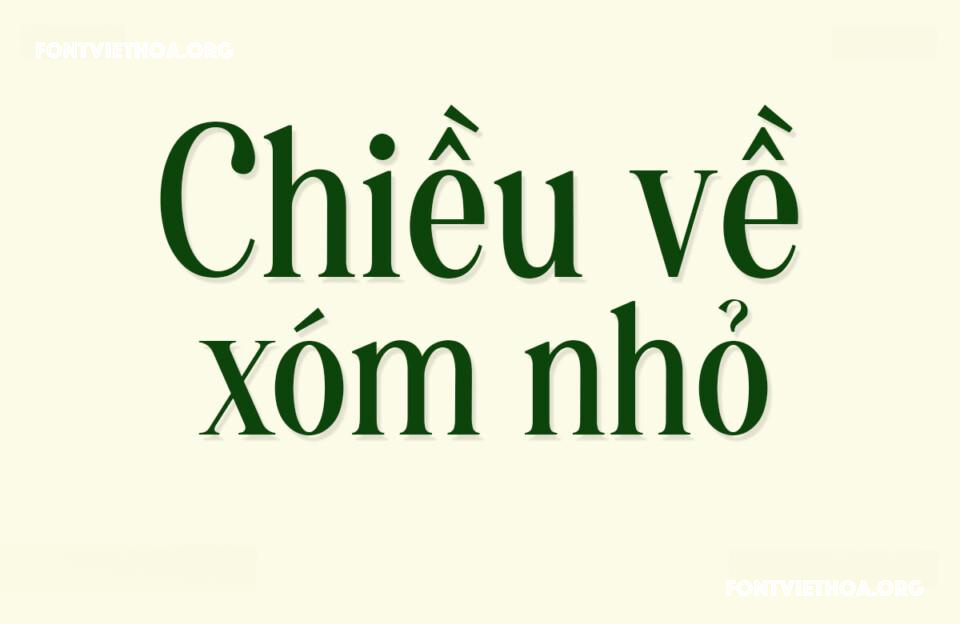
Tên font: Font Việt hóa VIP Destiny Gorgeous
Tác giả: HansCo
Font Việt hóa VIP Destiny Gorgeous là font chữ có chân, giúp bạn thoải mái dùng font chữ cho nhiều chủ đề thiết kế. Tự do sáng tạo và thể hiện phong cách riêng của bạn.
Font Việt hóa VIP Destiny Gorgeous là một trong những font chữ được yêu thích nhất hiện nay. Với thiết kế độc đáo và đẹp mắt, font chữ này giúp bạn tạo ra những thiết kế ấn tượng và thu hút.